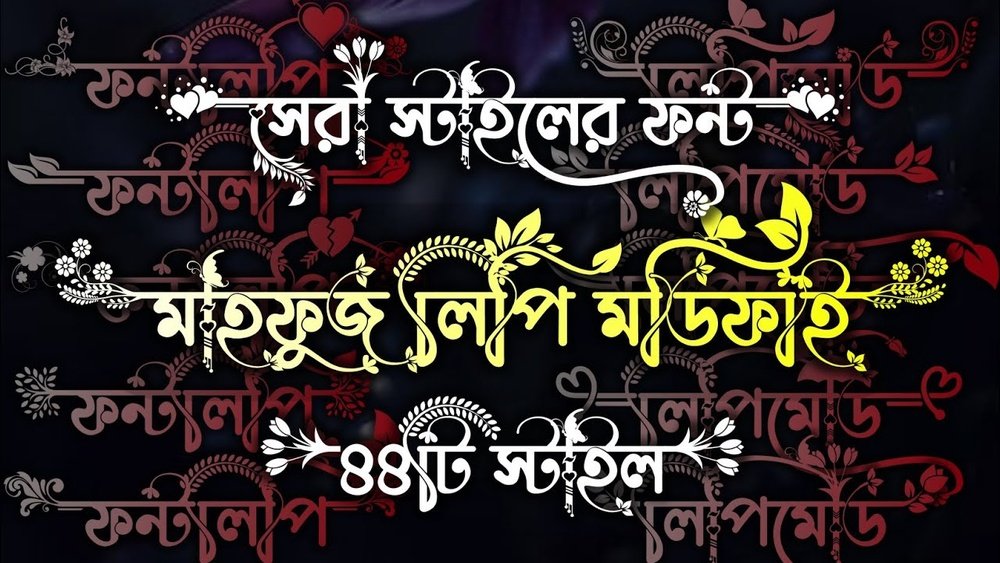
আপনি কি এমন একটি বাংলা ফন্ট খুঁজছেন যা আপনার ডিজাইন এবং লেখাকে আরও আকর্ষণীয় করে তুলবে? তাহলে “মাহফুজ লিপি বাংলা প্রিমিয়াম ফন্ট” আপনার জন্য আদর্শ সমাধান হতে পারে। এই ফন্টটি শুধু দেখতে সুন্দরই নয়, বরং এতে রয়েছে অনন্য স্টাইল এবং স্পষ্টতা, যা আপনার যেকোনো প্রকল্পে পেশাদারিত্ব যোগ করবে। আপনি চাইছেন আপনার ওয়েবসাইট, প্রেজেন্টেশন বা গ্রাফিক ডিজাইনে এক নতুন মাত্রা যোগ করতে?
তাহলে এখনই দেখে নিন মাহফুজ লিপি বাংলা প্রিমিয়াম ফন্ট কীভাবে আপনার কাজের মান বাড়াতে পারে। আপনার ডিজাইনের প্রতিটি শব্দ যেন জীবন্ত হয়ে উঠে, সেটাই এই ফন্টের মূল আকর্ষণ। বিস্তারিত জানার জন্য পুরো আর্টিকেলটি পড়তে থাকুন।
মাহফুজ লিপি বাংলা প্রিমিয়াম ফন্টের পরিচিতি
মাহফুজ লিপি হল একটি বাংলা প্রিমিয়াম ফন্ট, যা ডিজাইন এবং পাঠযোগ্যতার উপর বিশেষ গুরুত্ব দিয়ে তৈরি। এটি বাংলা লেখার জন্য আধুনিক ও পরিষ্কার একটি ফন্ট, যা বিভিন্ন ডিজিটাল ও প্রিন্ট মিডিয়ায় ব্যবহার উপযোগী।
এই ফন্টটি ব্যবহার করে বাংলা লেখা দেখতে হয় আরও আকর্ষণীয় এবং পেশাদার। লেখাকে সহজে বোঝার মতো করে তোলা হয়। তাই এটি লেখকদের, ডিজাইনারদের এবং বিভিন্ন প্রতিষ্ঠানের জন্য আদর্শ।
ফন্টের উদ্দেশ্য এবং ব্যবহার ক্ষেত্র
- উদ্দেশ্য: সহজে পড়ার মতো বাংলা ফন্ট তৈরি করা।
- প্রধান ব্যবহার: ওয়েবসাইট, ব্লগ, ডিজিটাল কনটেন্ট, পিডিএফ রিপোর্ট, বিজ্ঞাপন, ব্র্যান্ডিং এবং বই প্রকাশে।
- বিশেষত্ব: পরিষ্কার লেটার ফর্ম, যা ছোট থেকে বড় স্ক্রিনে সমান সুন্দর দেখায়।
কেন মাহফুজ লিপি ফন্ট জনপ্রিয় হচ্ছে?
- সুন্দর ও প্রফেশনাল ডিজাইন, যা চোখে পড়ার মতো।
- বাংলা লেখায় স্বচ্ছতা ও পাঠযোগ্যতা বাড়ায়।
- ডিজিটাল ও প্রিন্ট মিডিয়ায় সমান মানের ফলাফল দেয়।
- বাংলা ভাষাভাষীদের জন্য উপযোগী ও স্বাভাবিক লেআউট।
ফন্টটি বাংলা ডিজাইনের মান উন্নত করে। তাই অনেক পেশাদার ডিজাইনার ও প্রতিষ্ঠান এটি বেছে নিচ্ছে।
মাহফুজ লিপি ফন্টের অনন্য বৈশিষ্ট্যসমূহ
মাহফুজ লিপি বাংলা প্রিমিয়াম ফন্ট ডিজাইন ও ব্যবহারিক দিক থেকে বেশ অনন্য। এটি বিশেষভাবে তৈরি হয়েছে যাতে লেখার সৌন্দর্য বৃদ্ধি পায়। ফন্টটির মাধ্যমে বাংলা লেখায় আধুনিকতা ও পেশাদারিত্বের মিশ্রণ দেখা যায়।
ফন্টটি স্টাইলিশ ডিজাইন, প্রফেশনাল লুক এবং সুবিন্যস্ত অক্ষর বিন্যাসের মাধ্যমে পাঠকদের আকর্ষণ করে। প্রতিটি বৈশিষ্ট্য আলাদাভাবে ফন্টের মান বাড়িয়ে তোলে।
স্টাইলিশ ডিজাইনের মাধ্যমে ব্র্যান্ড ইমেজ বৃদ্ধি
মাহফুজ লিপি ফন্টের ডিজাইন অত্যন্ত স্টাইলিশ ও আধুনিক।
- সুন্দর ও আকর্ষণীয় অক্ষর যা যে কোনো ব্র্যান্ডের ইমেজ উন্নত করে।
- ফন্টের স্ট্রোক ও কার্ভগুলো সাবলীল এবং চোখে পড়ার মতো।
- বিভিন্ন ডিজাইন প্রকল্পে ব্যবহার উপযোগী।
প্রফেশনাল লুক যা পাঠকদের আকর্ষণ করে
- প্রতিটি অক্ষর পরিষ্কার ও স্পষ্ট।
- পাঠকদের চোখে সহজেই পড়া যায়।
- প্রেজেন্টেশন, রিপোর্ট ও ওয়েবসাইটে ব্যবহার উপযোগী।
ফন্ট ব্যবহার করলে লেখা আরও বিশ্বাসযোগ্য ও প্রভাবশালী হয়।
সুবিন্যস্ত অক্ষর বিন্যাস এবং পড়ার সহজতা
| বৈশিষ্ট্য | বর্ণনা |
|---|---|
| অক্ষর দূরত্ব | সঠিক দূরত্ব বজায় রেখে চোখে আরাম দেয়। |
| লাইন স্পেসিং | প্রতিটি লাইন স্পষ্টভাবে আলাদা থাকে। |
| পাঠযোগ্যতা | দীর্ঘ পাঠের জন্যও সহজ ও আরামদায়ক। |
মাহফুজ লিপি ফন্টের সুবিধা ও অসুবিধা
মাহফুজ লিপি বাংলা প্রিমিয়াম ফন্ট ডিজাইন ও ব্যবহারে বেশ জনপ্রিয়। এটি বাংলা লেখাকে সুন্দর ও স্পষ্ট করে তুলে ধরে। তবে, প্রতিটি ফন্টের মতো এটিরও কিছু সীমাবদ্ধতা রয়েছে। নিচে ফন্টটির সুবিধা ও অসুবিধা নিয়ে আলোচনা করা হলো।
মাহফুজ লিপি বাংলা প্রিমিয়াম ফন্ট লেখালেখিতে নতুন মাত্রা যোগ করে। এটি স্পষ্ট ও পড়তে সহজ, তাই যেকোনো ডিজাইন বা প্রকাশনার জন্য উপযোগী। বাংলা ভাষায় সুন্দর ও পেশাদার ফন্ট খুঁজছেন? তাহলে মাহফুজ লিপি বাংলা প্রিমিয়াম ফন্ট আপনার জন্য সেরা বিকল্প। সহজ ব্যবহার ও দৃষ্টিনন্দন ডিজাইনে ফন্টটি প্রতিদিনের কাজকে আরও আনন্দদায়ক করে তোলে। বাংলা লেখার মান উন্নত করতে এই ফন্টটি অবশ্যই ব্যবহার করুন।